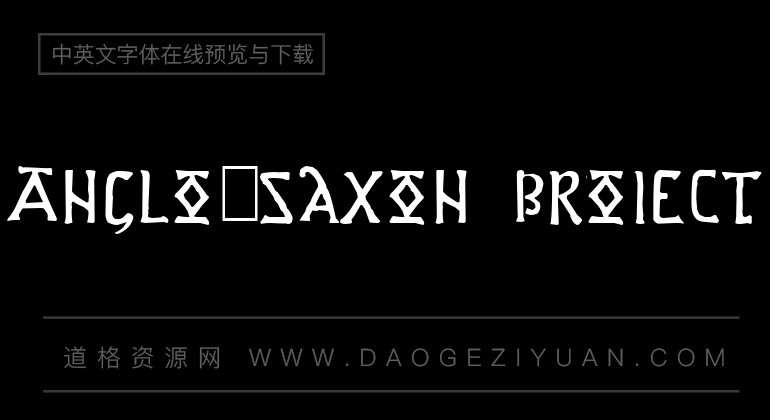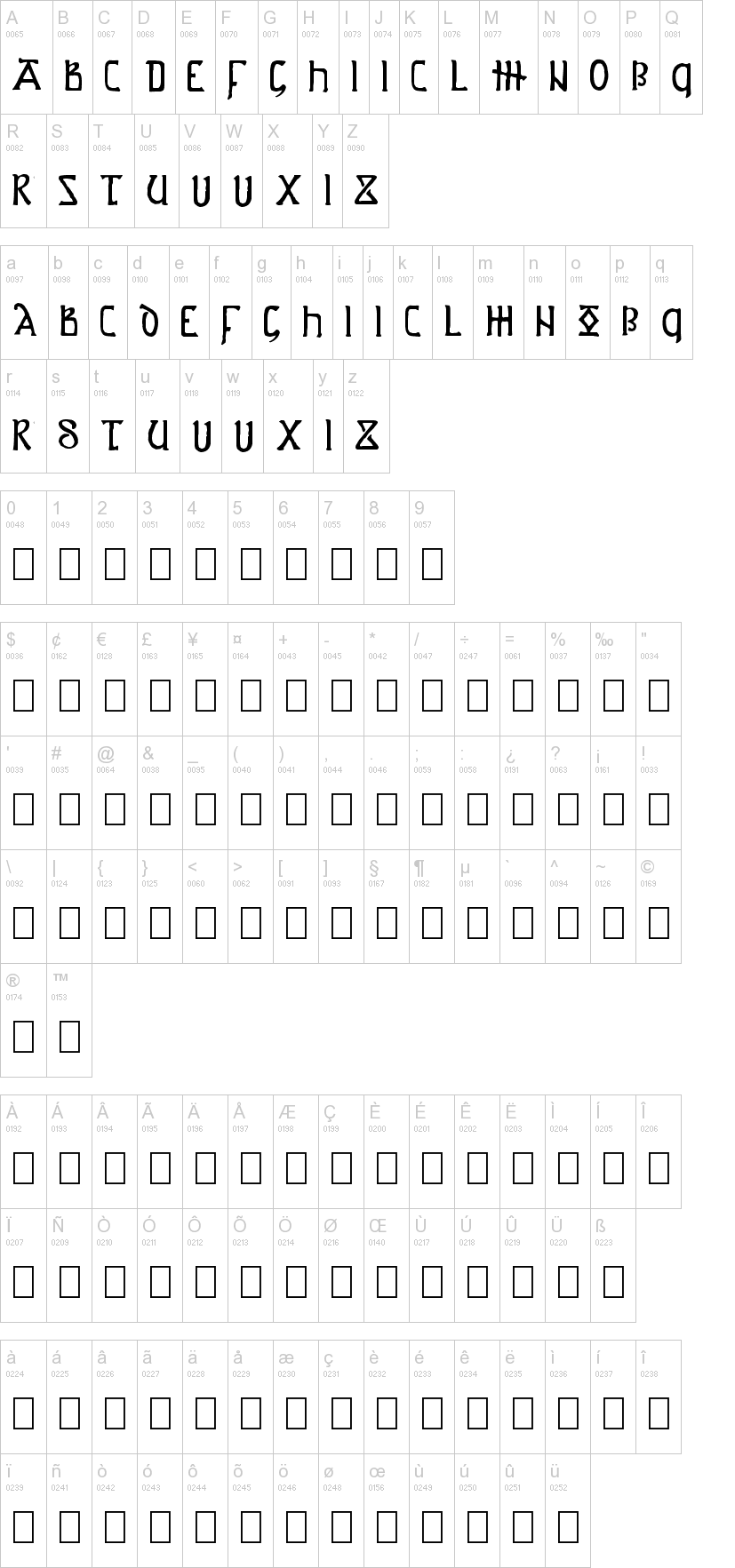
Anglo-Saxon Project
Anglo-Saxon Project 字体是一款由新英格兰字体设计师Bob Newman创作的经典字体。它的特点是以古老的英国文字为基础,结合现代英语的更新元素,构成一种独特的文字风格。它具有细腻的字符结构,拥有优雅的表现力和强烈的古典质感,是一款非常具有艺术性的字体。它可以用于商业广告,书籍封面,品牌标志,海报设计等多种应用场景,能够给设计师带来全新的灵感。
Anglo-Saxon Project是一款非常不错的手写艺术字体,具有很好的视觉感,适合于文化类的宣传设计、商业类品牌的广告和产品包装设计以及个性化文字排版等较多场景。
Anglo-Saxon Project字符映射图